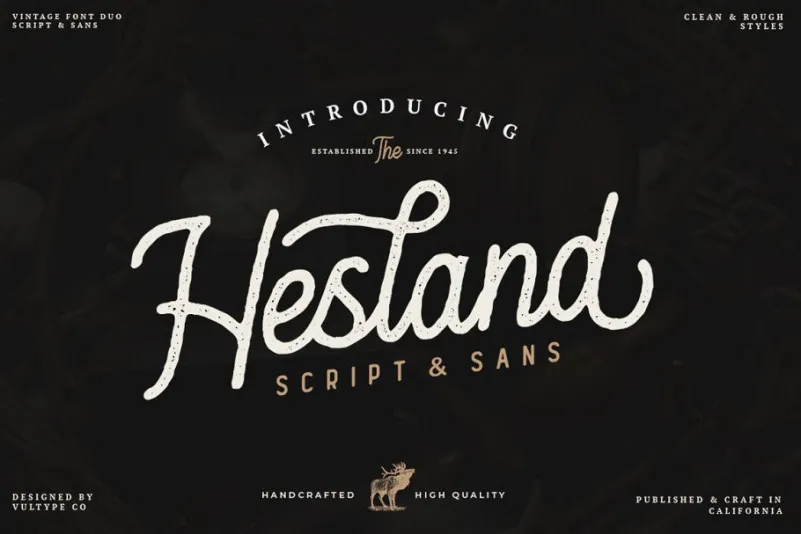
Hesland Vintage Font Duo – Download Grátis
A Hesland Vintage Font Duo é uma nova tipografia vintage projetada para capturar os detalhes mais delicados do passado, mas com um toque moderno. Inspirada na arte de impressão antiga americana, esta fonte traz uma aparência retrô, proporcionando um aspecto de qualidade handmade em cada letra. Com sua aparência suave e linhas perfeitas, a Hesland Vintage Font Duo é ideal para projetos que buscam um toque vintage sem perder a elegância moderna. Suas duas versões principais – Clean e Stamped – combinadas com o script e a sans serif, garantem que você tenha todas as ferramentas necessárias para criar uma experiência visual única. Perfeita para designers gráficos em busca de um toque vintage clássico e moderno, esta fonte é ideal para adicionar um quê de nostalgia a qualquer projeto. Não importa se estiver criando cartões de aniversário, design editorial ou letras digitais – a Hesland Vintage Font Duo tem o potencial de dar vida à sua arte através do tempo. Além disso, a combinação do script e da sans serif oferece flexibilidade ao designer. Você pode escolher entre um estilo retrô mais elaborado ou uma aparência mais minimalista dependendo das necessidades específicas do seu projeto. Seja você um amante dos detalhes ou aquele que prefere os designs simples, a Hesland Vintage Font Duo tem algo para todos.